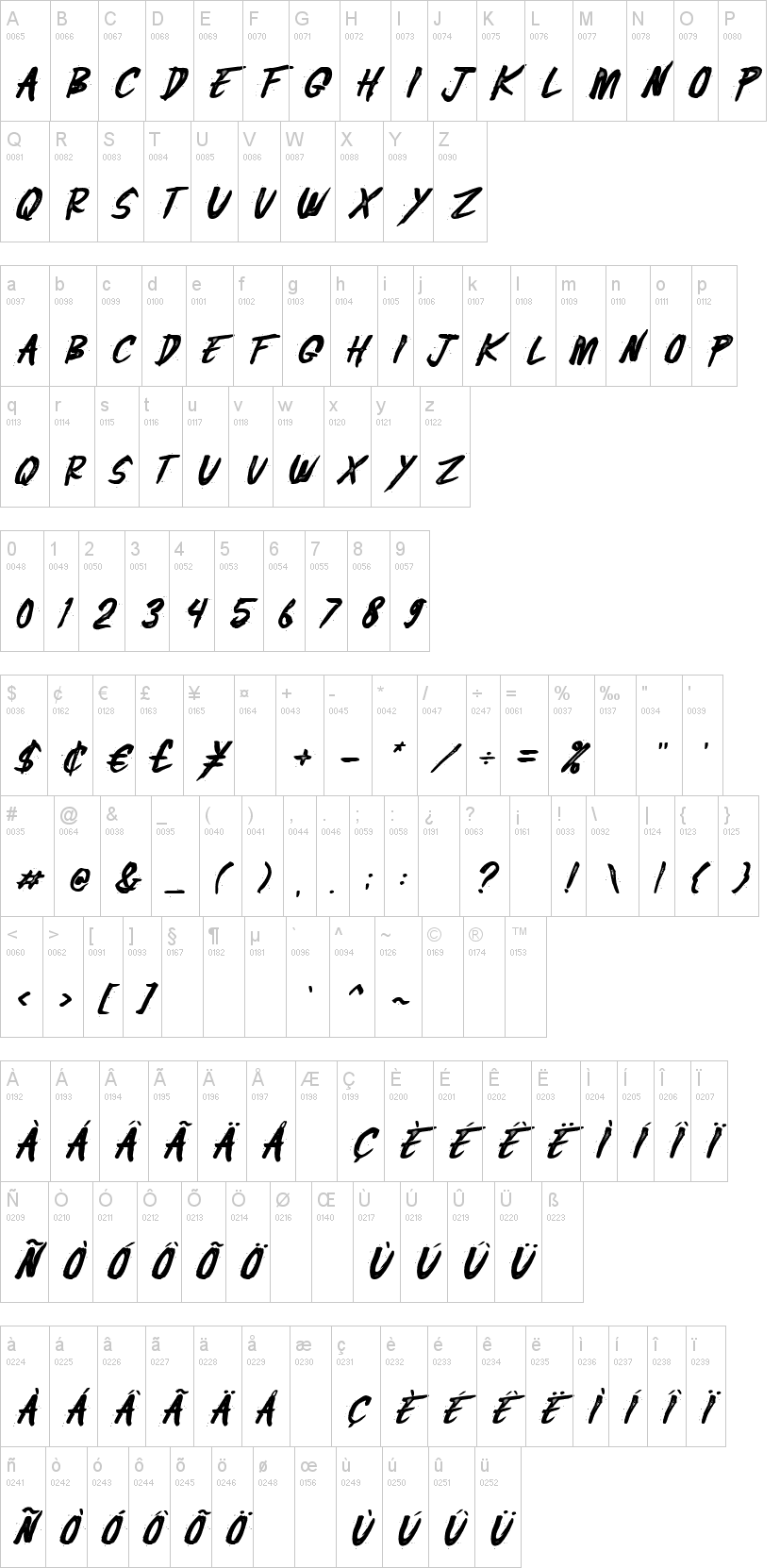
Rostoh 是一种现代风格的字体,具有高端和专业的外观。它由设计师Roman Paslavskiy创作,旨在为现代设计提供优秀的排版选择。 Rostoh 字体具有明显的特征,包括它的粗壮和坚定的外观,以及较宽的字母间距和笔画独特的设计。此外,该字体还具有一些优秀的特性,例如: - 可用于多种语言,并支持多种字母表和字符集 - 提供多种字重和风格,可用于不同的设计需求 - 具有良好的可读性和清晰度,即使在小字号下也能保持清晰和易读 总体而言,Rostoh 是一种坚固、现代、高质量的字体,适用于各种设计项目,例如标志、海报、招牌、书籍封面等。内容介绍
Rostoh是一款非常不错的手写艺术字体,具有很好的视觉感,适合于文化类的宣传设计、商业类品牌的广告和产品包装设计以及个性化文字排版等较多场景。